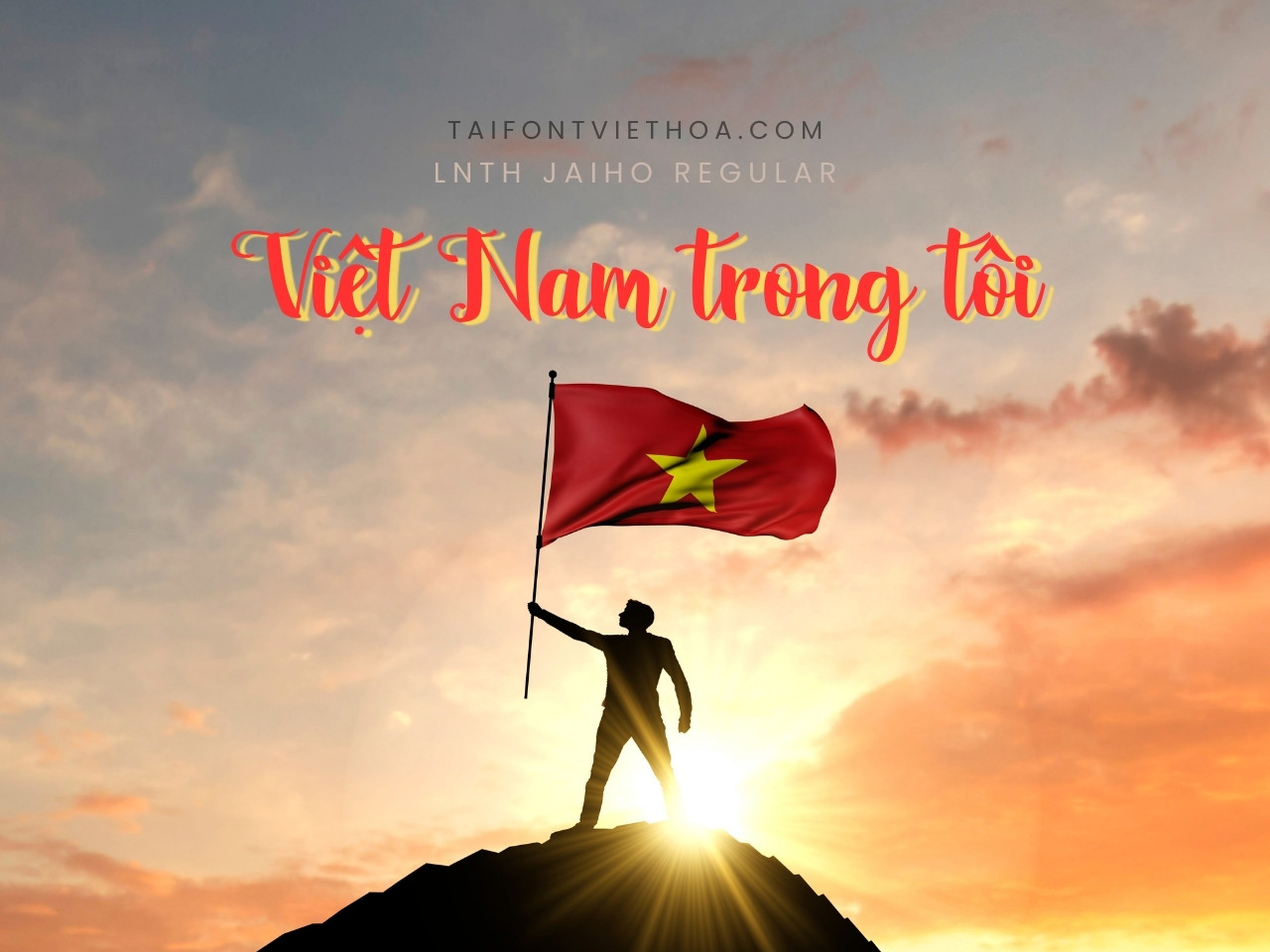
Font việt hóa LNTH Jaiho Script
Tác giả Font: Duo Font
Giới thiệu về font LNTH Jaiho Script – Viết tay hiện đại pha chất Á Đông lãng mạn
LNTH Jaiho Script là phiên bản Việt hóa của font “Jaiho Script” được thiết kế bởi Duo Font – một studio nổi bật với các thiết kế bay bổng, nữ tính và cảm xúc. Kiểu chữ này mang đậm phong cách handlettering hiện đại, đồng thời phảng phất chút tinh thần Á Đông nhẹ nhàng, nhờ vào các đường cong uốn lượn tinh tế. Phiên bản Việt hóa được thực hiện bởi Tuỳn Pucca, hỗ trợ đầy đủ tiếng Việt cùng hơn 60 ngôn ngữ khác – giúp font có thể dùng linh hoạt trong cả thiết kế nội địa và quốc tế.
Đặc điểm thiết kế và ứng dụng của LNTH Jaiho Script
LNTH Jaiho Script là kiểu font handwritten với các đường nét mềm mại, liên kết tự nhiên giữa các ký tự. Nét chữ uốn lượn, đậm vừa phải, tạo cảm giác như những dòng viết tay trôi chảy trên giấy. Font không quá phức tạp nhưng đầy tính nghệ thuật, nhấn mạnh yếu tố cá nhân và sự nhẹ nhàng tinh tế trong trình bày văn bản.
Font phù hợp cho các thiết kế như: thiệp cưới, bìa sách thơ, ấn phẩm handmade, blog cá nhân, truyền thông thương hiệu nữ, thiệp chúc mừng, bao bì mỹ phẩm thủ công hoặc các sản phẩm sáng tạo mang tính nghệ thuật. Ngành nghề ứng dụng: thời trang, giáo dục, mỹ phẩm, ẩm thực, đồ thủ công và truyền thông số hướng đến người dùng cá nhân hóa.